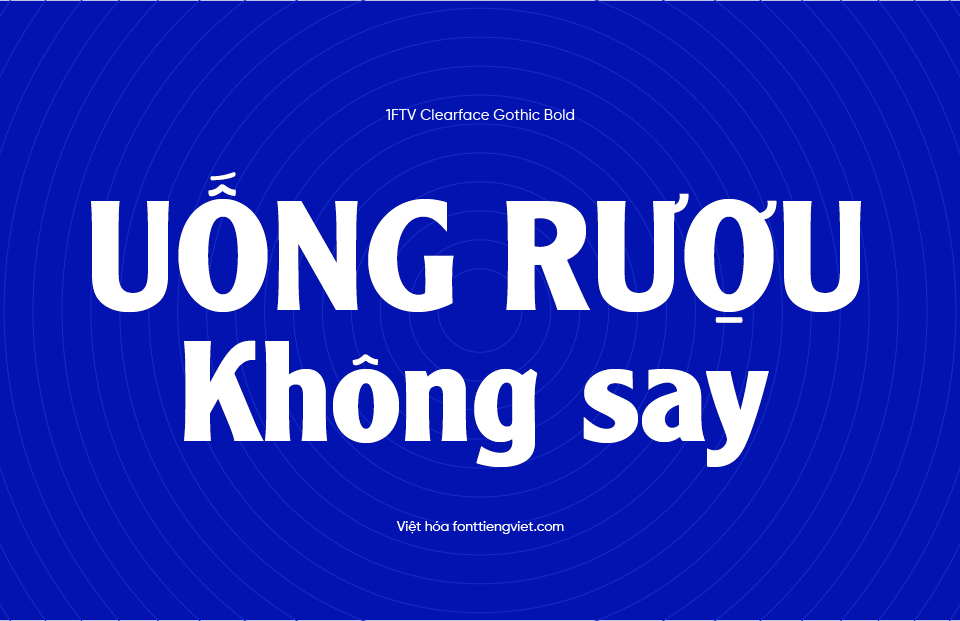
Font Việt hóa 1FTV Clearface Gothic Bold
Giới thiệu về Font Việt hóa 1FTV Clearface Gothic Bold
Trong thế giới thiết kế đồ họa hiện đại, việc tìm kiếm một bộ Font Miễn Phí chất lượng cao là ưu tiên hàng đầu của nhiều người. Font Việt hóa 1FTV Clearface Gothic Bold nổi bật như một giải pháp hoàn hảo cho các dự án đòi hỏi sự mạnh mẽ nhưng vẫn giữ được nét thanh lịch. Đây là phiên bản được tùy chỉnh kỹ lưỡng về dấu tiếng Việt, giúp các nhà thiết kế không còn lo lắng về lỗi hiển thị khi soạn thảo văn bản. Với độ dày đặc trưng của biến thể Bold, bộ chữ này mang lại khả năng đọc tốt ngay cả ở kích thước nhỏ hoặc trên các nền tảng kỹ thuật số phức tạp.
Đặc điểm nổi bật của Font Việt hóa 1FTV Clearface Gothic Bold
Thiết kế hiện đại và linh hoạt
Font Việt hóa 1FTV Clearface Gothic Bold sở hữu những đường nét kỷ hà chắc chắn, giúp tạo điểm nhấn thị giác mạnh mẽ. Cấu trúc chữ được tối ưu hóa để phù hợp với nhiều loại hình ấn phẩm từ tờ rơi, poster quảng cáo đến các slide bài giảng trong trường học. Sự cân bằng giữa các nét bo tròn và đường thẳng khiến bộ font này trở nên vô cùng thân thiện và chuyên nghiệp.
Ứng dụng thực tế trong giáo dục và sáng tạo
Nhờ tính ứng dụng cao, font chữ này thường được các giáo viên và học sinh ưu tiên lựa chọn để trang trí bảng tin hoặc làm tiêu đề cho các báo cáo sáng tạo. Sự rõ ràng của từng ký tự giúp nội dung truyền tải nhanh chóng và hiệu quả hơn bao giờ hết.